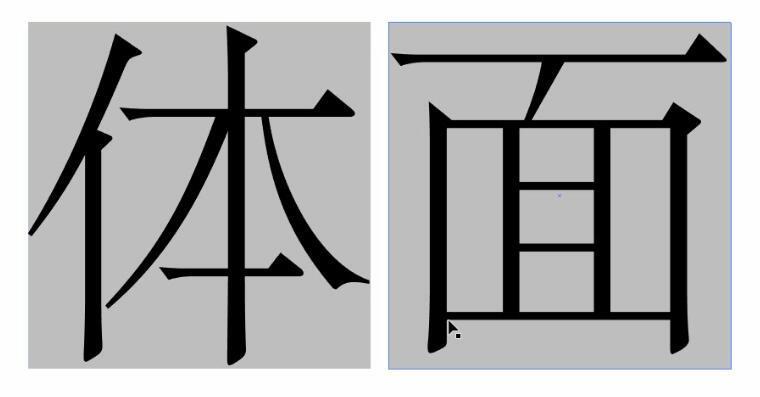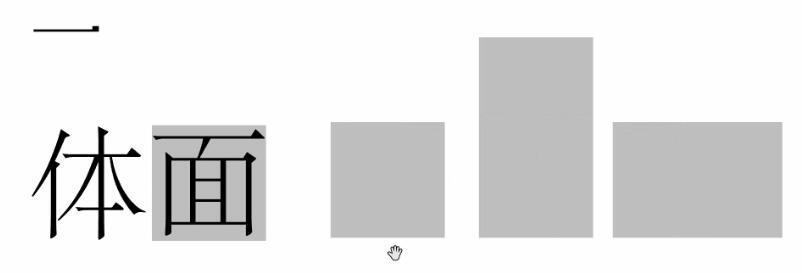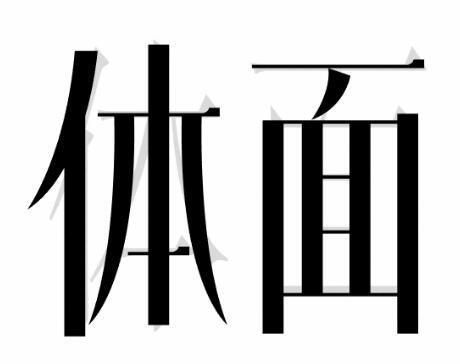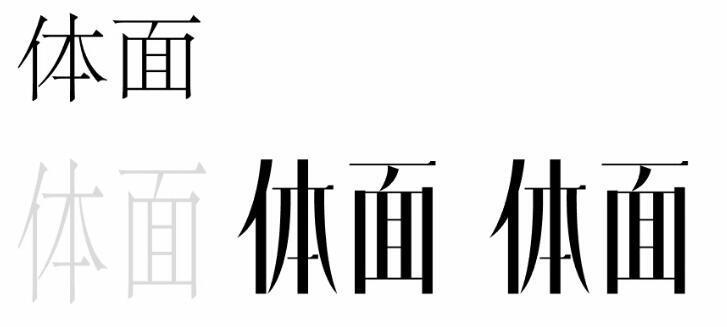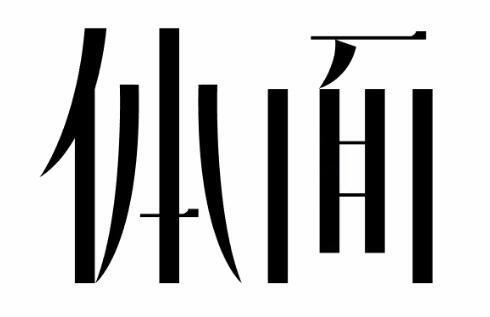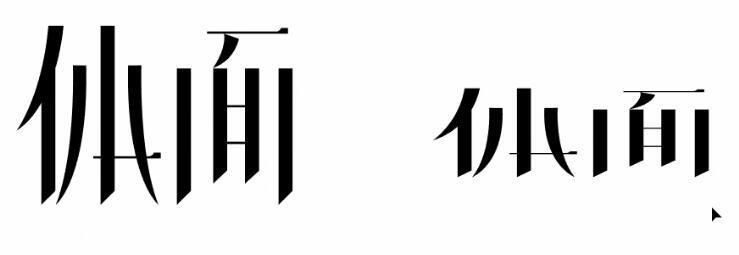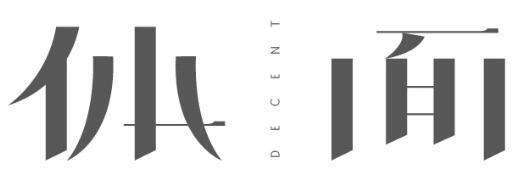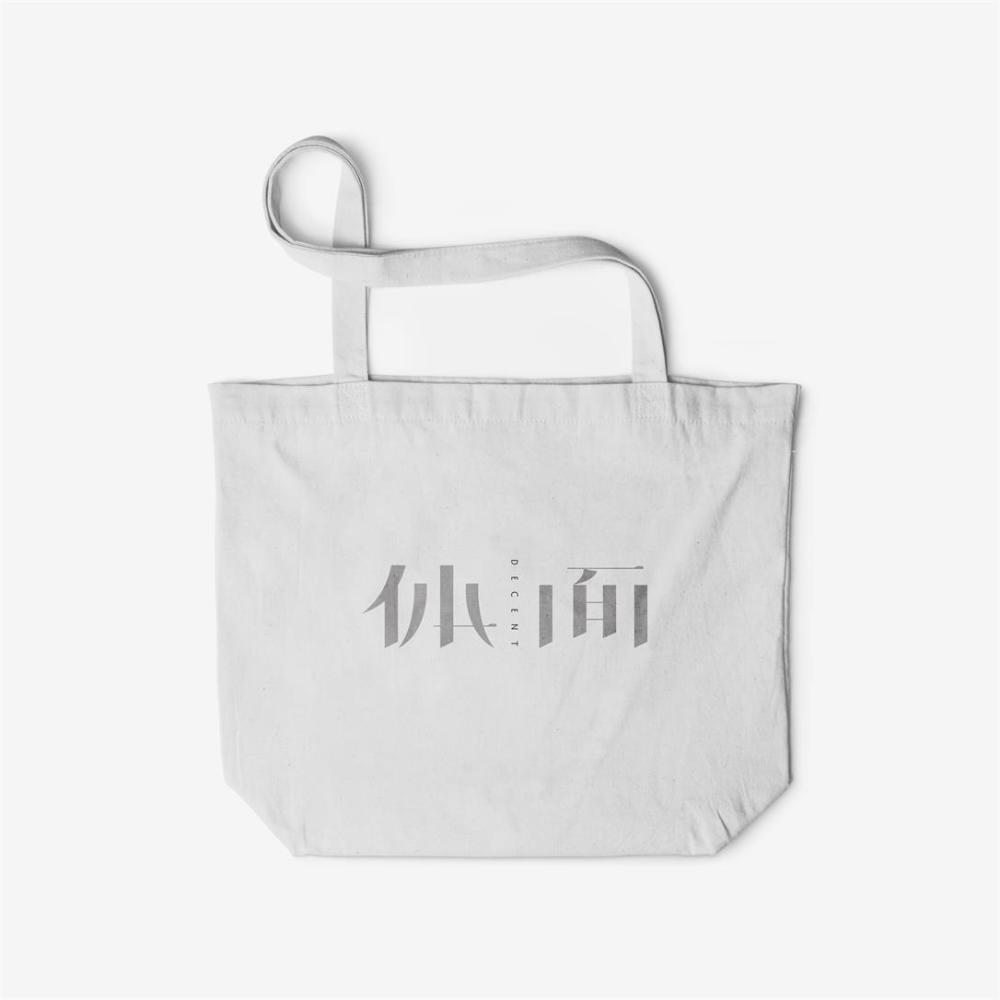
创意的字体如何设计?今天给大家带来的是一款字体设计的教程,既然要进行字体设计,那我们先来了解下常用字体的分类,常用字体的分类基本可以分为衬线字体与非衬线字体。其中非衬线字体主要以黑体类为主要大的代表,衬线字体在本节我以宋体来代表。
从上图中我们不难看出衬线字体与非衬线字体的区别,非衬线字体笔画规整,横竖笔画粗细相对比较统一,衬线字体则不同,一般横笔比竖笔要粗,并且会在起笔或笔末的端点添加装饰。如下图,通过不同装饰的添加可以表达不同情感和气质。
字体设计需要遵循4个原则:整体的统一2.方向的统一3.笔画上的统一4.空间上的统一。
本节课就以“体面”两个字为例,来进行字体设计。输入体面两个字,这些成熟的字体都比较完善,结构都是没有问题的,我们用矩形形状将字体框住,宋体的体面这两个字是正方形。
我们可以将字体形体上做变化,比如变宽变高
下方是我根据上述衬线字体的特点准备的笔画
用我们的笔画去替换原有笔画,我们可以在原有字体上展开设计,字体完善的结构保障我们设计中结构不会出问题,适合新手。
注意笔画上不要直接放大缩小,这样会影响的笔画的粗细,可以直接复制原有笔画,调整长短,更能保证笔画的统一
我们把设计的字体拿到一边,可以看到已经找不到之前宋体的影子啦。
现在形态已经出来啦,但是显着太过普通没有设计感,还是停留在基础阶段,下面我们采用一些常用的设计手法来使字体产生变化
比如省略,汉子的识别是不需要完整笔画就能识别出来的,即使出现部分我们同样能够识别字体,俗称脑补。当然也可能补错,大家不要破坏重要笔画
我砍掉了部分笔画,你会发现你仍然是可以识别
继续细化,这次选择笔画的斜切,并且将字体压扁,这样好像更符合字体的气质
最后适当添加装饰,我用了大写的英文字母,看起来比较精致一些,到这里完成字体的设计
找个手提袋看下它的应用效果